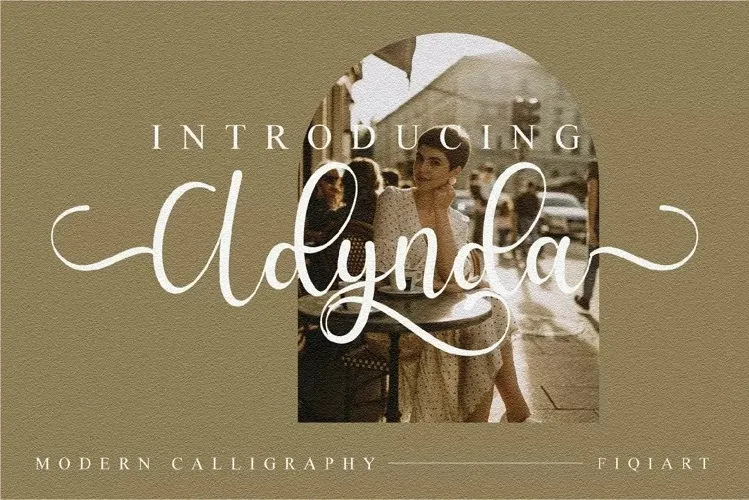
Adynda Font – Fonte Grátis
Adynda Font
A Adynda Font é uma elegante escolha para os designers que buscam uma fonte script moderna e vibrante. Criada pela artista fiqiart09, essa fonte adota características de cintilância única, proporcionando um toque moderno sem abandonar o encanto autêntico do estilo script. Dotada de uma compreensão cuidadosa dos detalhes, esta font foi projetada para trazer brilho e sofisticação a qualquer projeto gráfico que use. Com seu formato equilibrado e variado, Adynda se destaca como uma excelente opção para aqueles buscando um toque fresco e único em seus trabalhos. Ideal tanto para criar mensagens elegantes quanto para adicionar uma pitada de criatividade às suas identidades visuais, esta font será um acréscimo impecável à sua coleção de recursos gráficos.